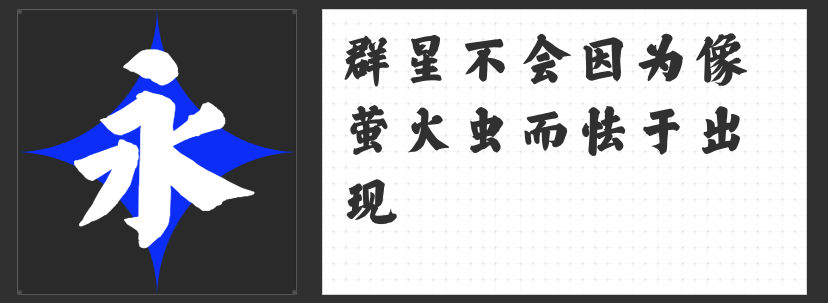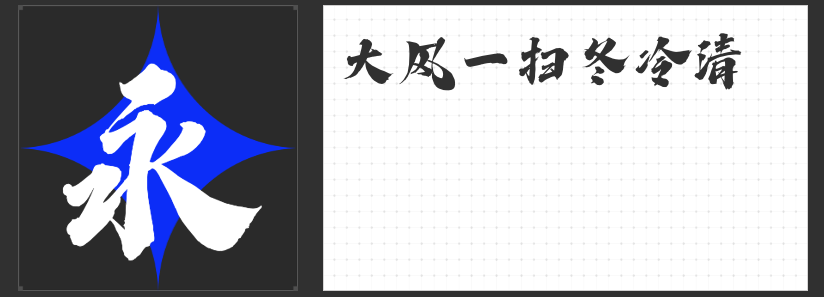
四款书法字体推荐:以笔墨韵味重塑设计灵魂
在视觉设计中,书法字体以其独特的艺术感染力,为品牌标识、文化海报及艺术创作注入东方美学意蕴。本文精选四款非免费书法字体,涵盖行书、楷书、舒体等多元风格,助力设计师以笔墨语言传递品牌温度与文化深度。
一、 高手字斋树高行书
高手字斋树高行书以“行云流水”为核心理念,笔画连绵如丝,气韵贯通,既有行书的洒脱灵动,又暗含草书的奔放气度。其字形结构疏密有致,提按转折间尽显笔锋韵律,适用于茶饮品牌、文化展览海报及古风主题包装设计。该字体在动态海报中可强化视觉张力,在静态印刷品中则能营造悠远意境,是传递东方美学意境的绝佳选择。
二、 励字舒体简繁
励字舒体简繁融合楷、行、隶、草、篆五体之长,字形飘逸而不失筋骨,既有颜真卿楷书的浑厚雄强,又含柳公权书法的峭拔风骨。其笔画如弯弓盘马,刚劲中见柔美,恣肆中透逸气,适用于高端酒类包装、艺术展览主视觉及文化纪录片标题设计。该字体通过传统与现代的平衡,既能彰显品牌的文化底蕴,又能契合当代审美趋势。
三、 高手字斋树高大楷
高手字斋树高 大楷以“圆润娟秀”为风格基调,笔画饱满丰润,结构端庄严谨,却在细微处暗藏灵动变化。其字形如美人临风,既有楷书的规整之美,又含行书的流动之韵,适用于教育机构品牌、文创产品包装及古籍出版封面设计。该字体在保持传统楷书规范性的同时,通过笔画的细微起伏赋予视觉呼吸感,适合需要传递文化厚重感的设计场景。
四、创客贴劲书体
创客贴劲书体以“潇洒不羁”为设计语言,笔画刚劲如刀刻斧凿,字形结构大开大合,充满力量感与速度感。其风格融合现代审美与传统书法精髓,适用于运动品牌、科技产品发布会及潮流文化活动视觉设计。该字体在动态视觉中可强化冲击力,在静态排版中则能凸显品牌个性,是打破传统书法字体刻板印象的创新之作。
四款书法字体各具特色。设计师可根据品牌调性与项目需求,选择适配字体,让笔墨韵味成为视觉叙事的灵魂载体。